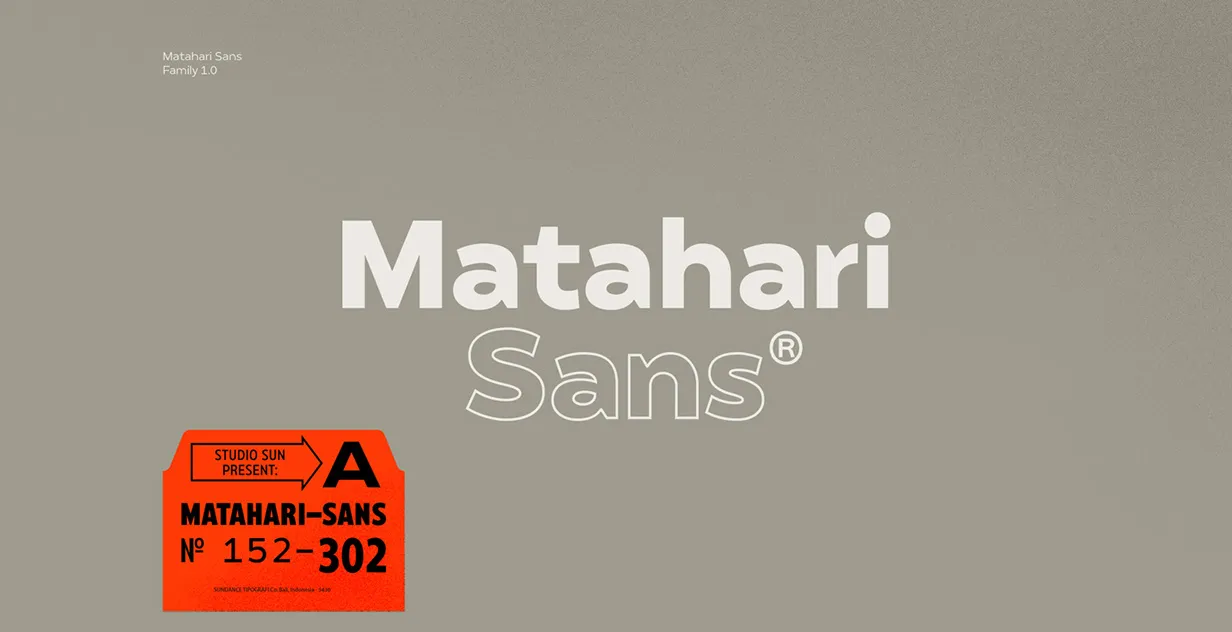
Font Tiếng Việt Matahari Sans Font Family (52 font) – Bộ Font Đa Năng Cho Thiết Kế Chuyên Nghiệp
Trong thế giới đồ họa hiện đại, việc tìm kiếm một bộ Font Miễn Phí chất lượng và hỗ trợ đầy đủ tiếng Việt luôn là ưu tiên hàng đầu của các nhà thiết kế. Font Tiếng Việt Matahari Sans Font Family (52 font) nổi lên như một giải pháp toàn diện, đáp ứng mọi nhu cầu từ trình bày văn bản hành chính đến sáng tạo các ấn phẩm quảng cáo nghệ thuật. Với số lượng biến thể khổng lồ, bộ font này giúp người dùng dễ dàng tùy biến giao diện đồ họa một cách linh hoạt và đồng nhất.
Khám phá hệ sinh thái Font Tiếng Việt Matahari Sans Font Family (52 font)
Matahari Sans không chỉ đơn thuần là một kiểu chữ, mà là một hệ thống thiết kế đồ sộ. Font Tiếng Việt Matahari Sans Font Family (52 font) bao gồm nhiều độ dày khác nhau từ Thin, Light đến Bold và Black. Điều này cho phép bạn tạo ra sự phân cấp thị giác rõ ràng trong bài giảng hoặc báo cáo trường học.
Ưu điểm vượt trội của bản Việt hóa
Phiên bản này đã được tinh chỉnh kỹ lưỡng về các dấu thanh tiếng Việt, đảm bảo không bị lỗi hiển thị khi gõ trên các phần mềm phổ biến như Photoshop, Canva hay Word. Độ tương phản thấp và cấu trúc hình học của font giúp người đọc không bị mỏi mắt, rất phù hợp cho các tài liệu giáo dục dài tập.
Ứng dụng thực tế của Matahari Sans trong học tập và công việc
Nhờ tính đa dụng, bộ font này thường được sử dụng để làm tiêu đề báo tường, thiết kế slide thuyết trình sinh động hoặc trình bày các đồ án tốt nghiệp. Sự tinh tế trong từng nét chữ giúp sản phẩm của bạn trở nên hiện đại và chuyên nghiệp hơn hẳn các font mặc định thông thường.
Kết luận về bộ font đa năng